Каллиграфия. Рукописные шрифты Запада и Востока
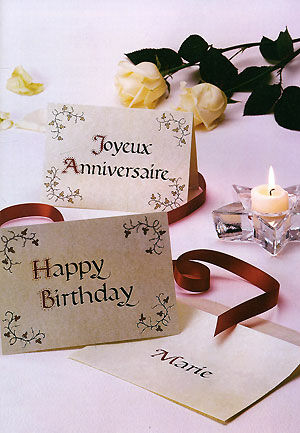
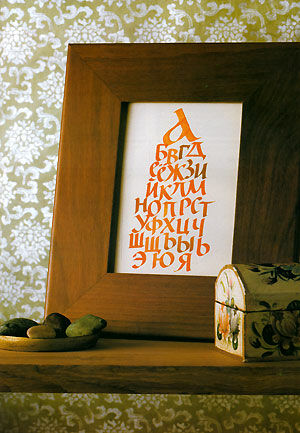
The Complete Guide to Calligraphy
Книга написана коллективом хорошо известных в области каллиграфии специалистов и содержит подробные пошаговые указания, которые помогут вам освоить основные рукописные шрифты, встречающиеся в письменности различных культур и стран:
- Классические вариации кириллицы.
- Латинские шрифты, включая каролингский, римскую капитель, унциальный, готический, курсивный и копперплейт.
- Другие виды письма, в том числе древнегреческое, иврит и арабскую вязь.
- Пиктографические виды письма - китайские и японские иероглифы.
В книге подробно рассматривается история возникновения и развития каждого шрифта, также приведен компактный, но очень удобный словарь принятых в каллиграфии терминов.
Освоить каждый из предлагаемых шрифтов вам помогут интересные проекты, которые также послужат гениальными идеями для подарков.
Среди них вы найдете:
- Пригласительные открытки.
- Оберточную Бумагу, керамическую плитку, шкатулки.
- Вставленные в рамку надписи, веера, абажуры и многое другое!
Книга рассчитана как на опытных, желающих повысить свое мастерство каллиграфов, так и на тех, кто только делает первые шаги на пути изучения уникального древнего искусства каллиграфии.